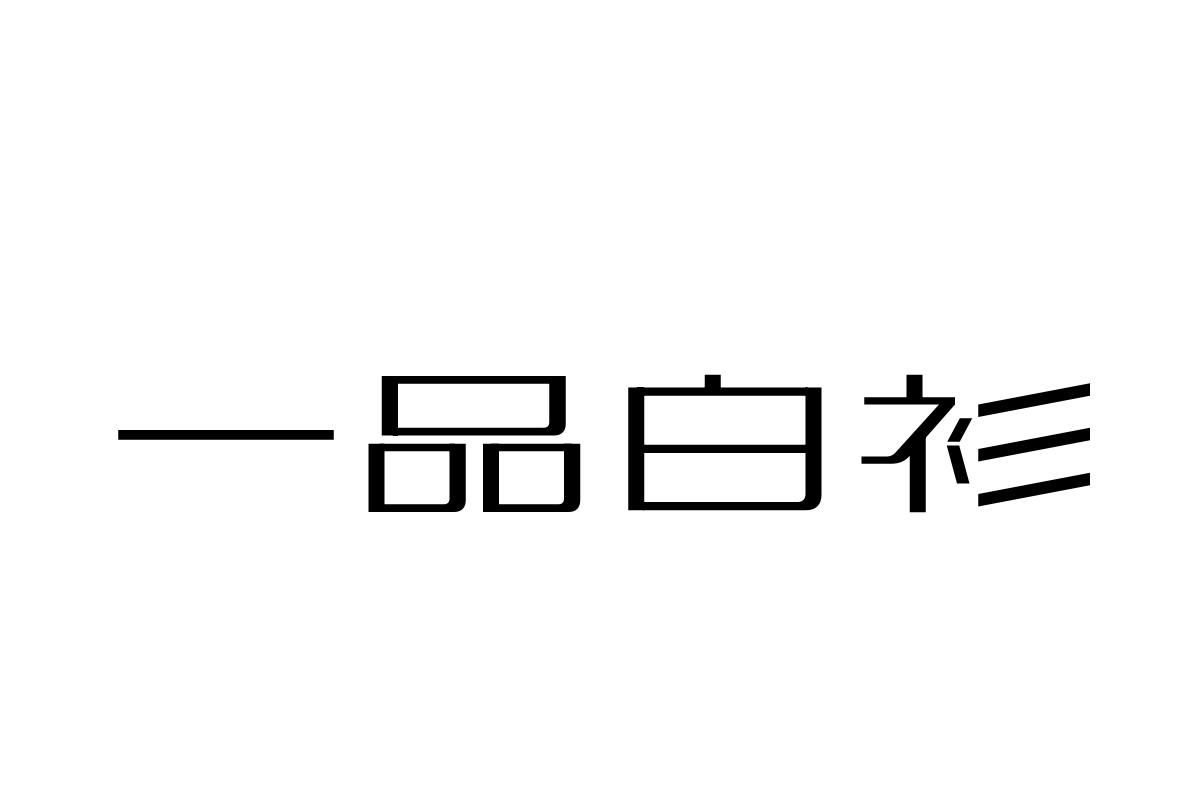
三极刃黑是一种细体中文字体,具有独特的设计和风格。这种字体的特点是线条流畅、清晰,给人一种简洁、现代的感觉。它的笔画粗细适中,既有力度又不失美感,适合用于需要强调细节和表达精确的场合。
三极刃黑采用了传统的书法线条,但对其进行了现代化的处理,使其更加符合现代审美。它的字形结构紧凑,每个字都显得非常精致,仿佛经过精心雕琢而成。这种字体不仅适用于印刷品,也非常适合用于网页设计、广告牌等视觉传达领域。